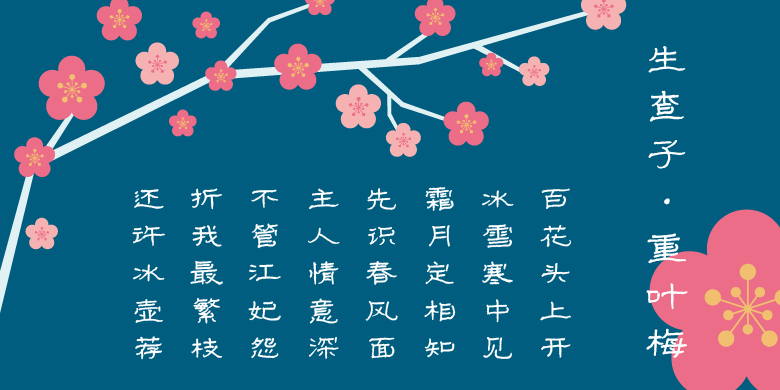
方正字迹-兰梓硬笔隶书
字体品牌: 方正字迹 设计师:张惟梓 字体分类:隶书 字体属性:精品字 字符集:大陆简体(GB2312-80) 发布时间: 2020
该款隶书取法汉隶名帖《礼器碑》,用硬笔书写,笔画更加瘦劲,线条更加凝练。将笔画的粗细、方圆,笔势的动静、向背完美地统一在一起。其结体严谨,字法规范,清超遒劲,庄重典雅,高古且充满逸趣。适用于文化类产品的包装宣传设计等。
作者张惟梓,擅长绘画、摄影及美术字设计等,长期从事企业文化、宣传及产品设计开发工作,摄影及美术作品曾多次参加省市级展览。